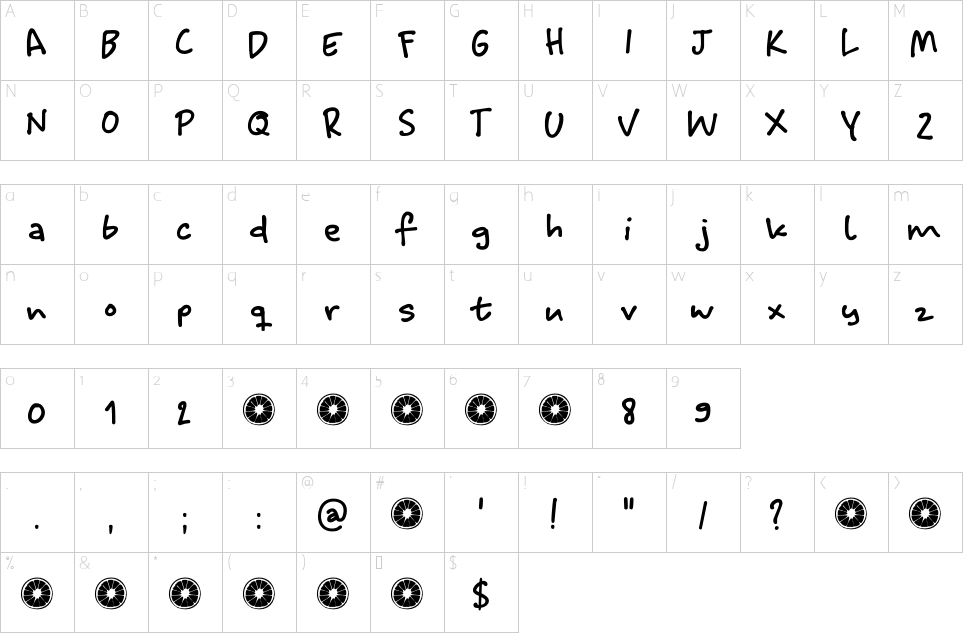
A fonte Juicer é uma excelente adição para seu portfólio de designers gráficos, oferecendo uma aparência fresca e moderna que certamente se destacará em qualquer projeto. Desenvolvida pelo designer Hanoded, a fonte Juicer está disponível gratuitamente tanto para Windows quanto para Mac. Com um design minimalista e arredondado, ela é perfeita para criar títulos e headlines atraentes. Seu tamanho de fonte variável facilita a criação de textos de qualquer tamanho sem perder a qualidade do design, tornando-a perfeita para aplicações de design, gráficos e criação de conteúdo digital. Com apenas 116 downloads, a fonte Juicer continua a atrair designers de todo o mundo. Embarque nessa e descubra por si mesmo a beleza e versatilidade desta fonte.